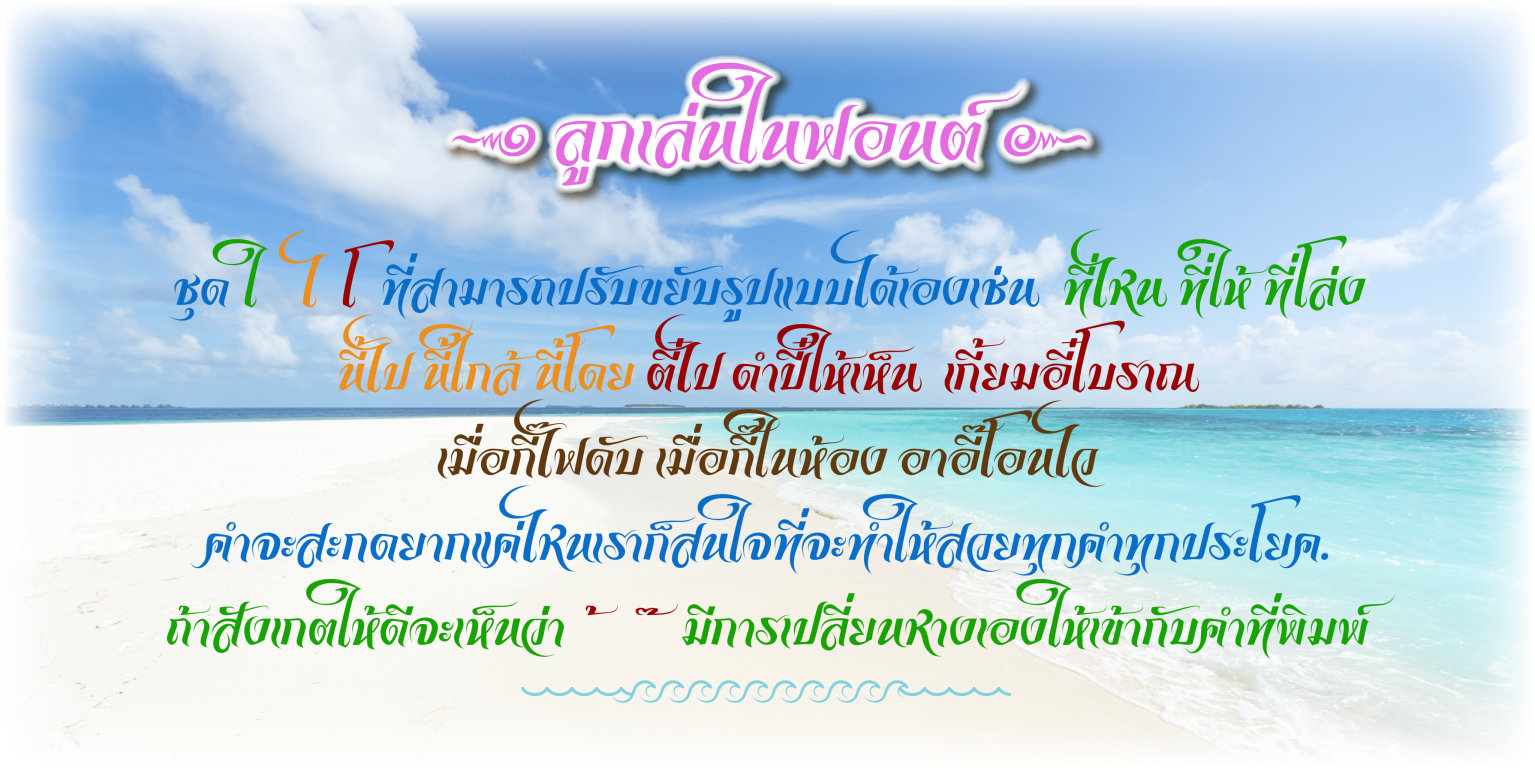
ฟอนต์เธอ
ชื่อฟอนต์ เธอ
ลักษณะฟอนต์ไทย เล่นหาง พาดหัว หรือ เนื้อหาบทความได้ งานป้าย บทกลอน
ร้านทอง สายมู ปกนวนิยาย พระเครื่อง โบราณ แสดงความเป็นเอกลักษณ์ไทยร่วมสมัย  อ.จินดา เนื่องจำนงค์ ฯลฯ
ฟอนต์ตัวนี้อักษรภาษาไทยเริ่มต้นจาก ลายมือของท่าน อ.จินดา เนื่องจำนงค์ ผมมองแล้วชอบตัว "ธ" ที่มีเอกลักษณ์ก็เก็บมาคิดตีความใหม่โดยวาดขึ้นให้มีกลิ่นไอของลายมือท่าน อ.จินดา เนื่องจำนงค์ ส่วนตัวอักษรอังกฤษ ตัวเลข และสัญลักษณ์ประดิษฐ์เขียนขึ้นใหม่ทั้งหมด ส่วนที่ยากของฟอนต์ตัวนี้คือลูกเล่นที่เวลาพิมพ์แล้วให้มันลงตัวดูสบายตา มีความยืดหยุ่นในส่วนที่ผู้ใช้ปรับเองได้ตามรูปที่แนบมาด้วย เลยตั้งชื่อฟอนต์ที่ผมประทับใจกับตัวอักษร "ธ" เลยตั้งเป็นชื่อฟอนต์ " เธอ ".
ลูกเล่นในฟอนต์  :45:
ลูกเล่นยังเป็นเช่นเดิมตามคอนเซปต์ Devilfont
* ใช้งานด้วย kerning ประระยะห่างของชุดอักษรทั้งไทย-อังกฤษ
* ใช้ mark ในการจัด อักษร+สระ+วรรณยุกต์ เพิ่มการไล่ระดับสระ+วรรณยุกต์ อัตโนมัติ
* เพิ่มลูกเล่นที่ โ ใ ไ ที่ยืด-หด ความสูงในเวลาพิมพ์อัตโนมัติเมื่อ
เจอวรรณยุกต์ชั้นบน เช่น ที่ไป ชี้ให้ ตี๋ให้ / ไม้โทเปลี่ยนหางเองได้ ไม้ตรีเปลี่ยนหางเองได้
* ปรับหางยาวเองเมื่อสะกดด้วยไม้หันอากาศ ปัฝัฟัศัสัฮั ด้วยการกด ฯฯ ตามหลัง ปฝฟศสฮ
* ปฝฟศสฮ อยากปรับให้หางยาวสวยขึ้นด้วยการกด ฯฯ ตามหลัง เช่น ปฯฯ
* สระ อิอีอึอื ขยับลดความยาวได้กด ฯฯ  ฯฯฯ  ตามหลัง ดูตัวอย่างได้จากรูปที่แนบมา
* ว ลดหางหลบให้สระอุอู  /  ห เปลี่ยนรูปเองหลบสระวรรณยุกต์
* ชุด การันต์  ขยับเปลี่ยนไม่ให้ชนกับสระอิอีอึอื ที่ตามหลัง ดูตัวอย่างได้จากรูปที่แนบมา
* ฉ ณ น เปลี่ยนรูปเมื่ออยู่ท้ายสุดหรือเจอกับสระ อา สระ อำ . , : ;  ดูตัวอย่างได้จากรูปที่แนบมา
* ส ล  เมื่อเจอสระ อุ อู จะเปลี่ยนรูปเป็นหัวเล็กลง
* เพิ่มวิธีการพิมพ์ โคมูตร ( ๛ ) กด  ฯ147963 ต้องการโคมูตรตัวพิเศษกลับด้าน 147963ฯ
* เพิ่มวิธีการพิมพ์ตัวบาลี ญ ฐ แบบไม่มีเชิง ด้วยการกด ญฯฯ  /  ฐฯฯ  จะได้ตัวที่ไม่มีเชิง
* ชุดตัวอักษรอังกฤษ เปลี่ยนรูปแบบอัตโนมัติ
* ปล. ยังมีลูกเล่นซ่อนอยู่อีก...ฯลฯ